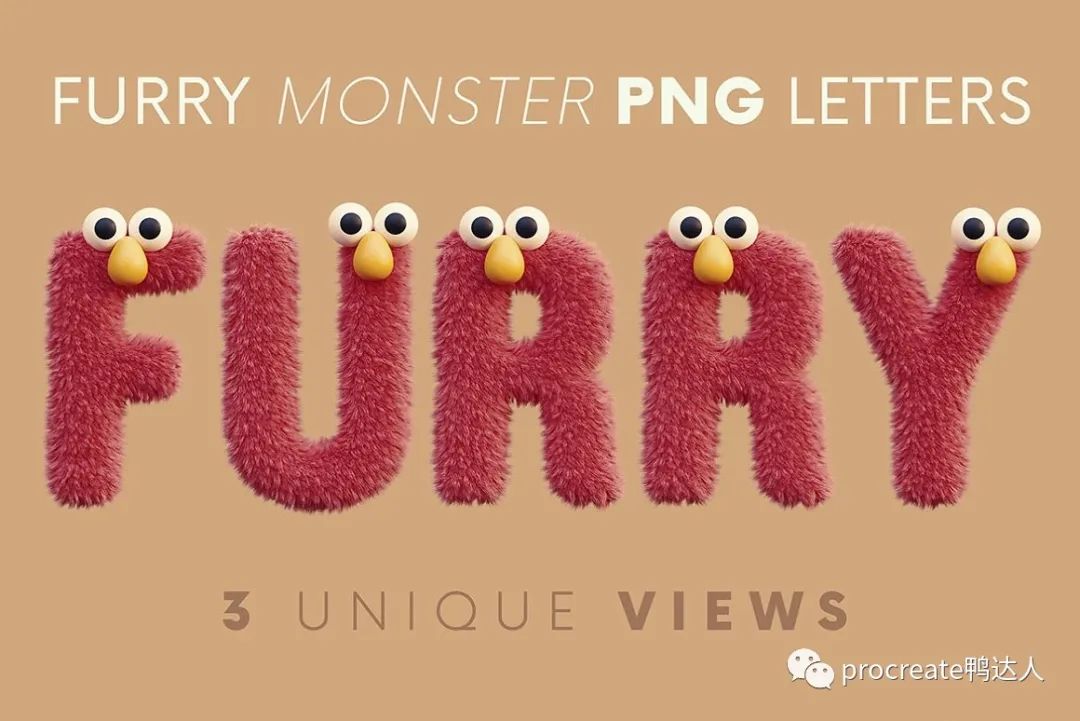
3D搞怪毛绒质感的装饰字体来啦,作品瞬间有趣了【740期】
一套3D渲染毛绒质感,可爱俏皮的卡通毛怪英文装饰字体,造型活泼俏皮,引人注目。包含了26个大写字母、10个数字,以及一些常用的基本符号,尺寸为3000×3000 px。所有字体均为png透明背景图片,有三种不同角度视觉效果可供选择,颜色也可以根据需要修改。适用于电影海报、广告宣传、专辑封面、杂志封面等。01 装饰字体使用效果
高分辨率和逼真的 3D 有趣、俏皮或毛茸茸的怪物刻字渲染(3000×3000 像素 – 但字母尺寸小一点)。
装饰字体预览